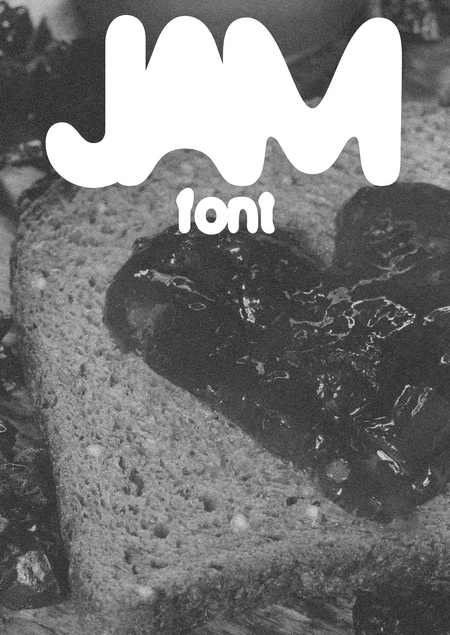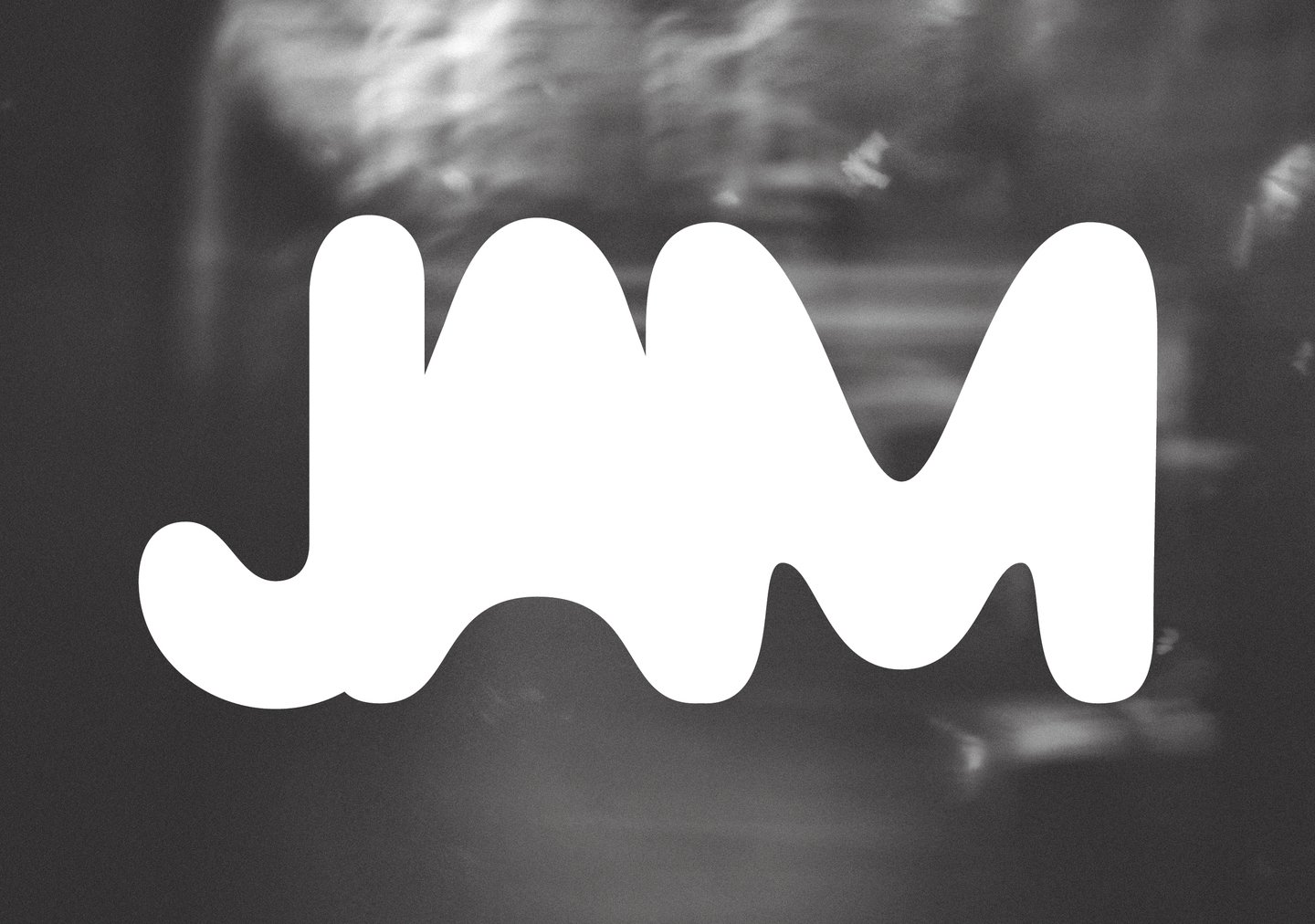
JAM font
JAM — это шрифт, вдохновлённый вареньем: расплывающимся, тягучим, но при этом упругим, таким, какое делает моя бабушка. Меня интересовало это состояние между формой и текучестью, когда масса уже начинает плыть, но всё ещё держит внутреннее напряжение.